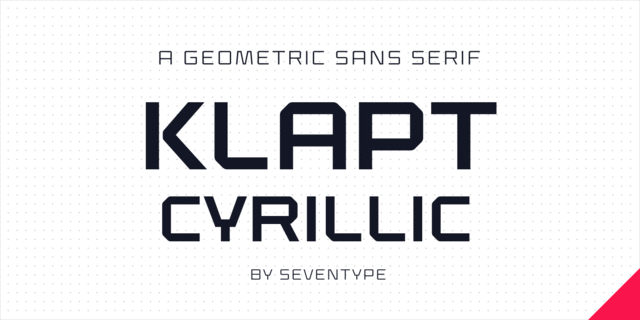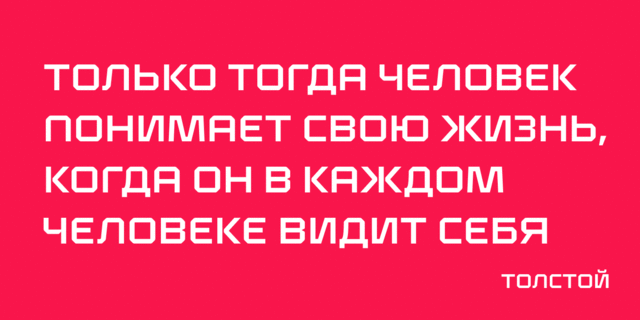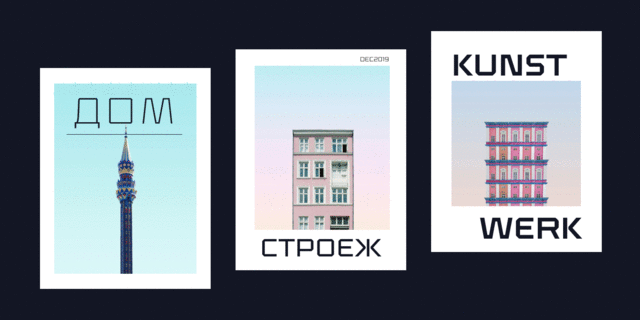
Klapt Cyrillic – это расширенная версия геометрического гротеска Klapt. Семейство из четырех начертаний включает расширенный набор символов, поддерживает большинство языков на латинице, кириллицу и даже вьетнамский язык! Этот шрифт может быть и жирным и очень тонким, предназначен для различного дизайна, от брендинга и фирменного стиля до многостраничных изданий для печати и экранов. Он отлично подходит для акциденции, особенно для заголовков, постеров, журналов, обложек, логотипов. Не стесняйтесь делиться своими дизайнами с использованием Klapt Cyrillic или просто свяжитесь с автором . Шрифт разработала Витория Невес в 2019 году.
Ассоциации c начертанием Klapt Cyrillic LightКачества и характер:
ровный, квадратный, точный, логичный, холодный, автоматический, техногенный, твердый, статичный, резкий, четкий, устойчивый, стабильный, тонкий, легкий, прямоугольный, городской, современный, машинный, острый, инженерный, урбанистический, чертежный, стеклянный, хрупкий, футуристичный, проволочный